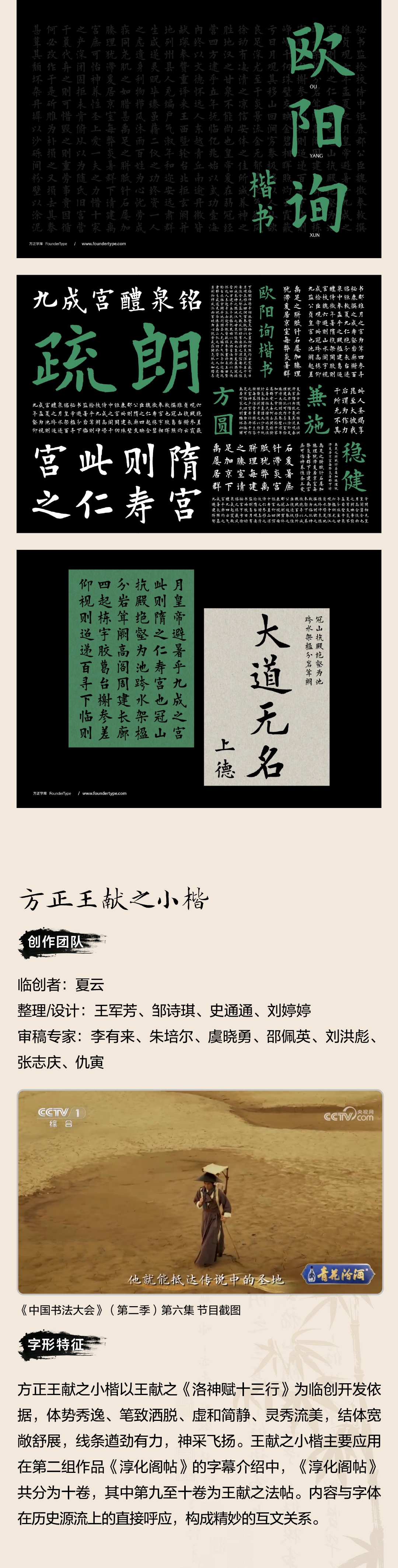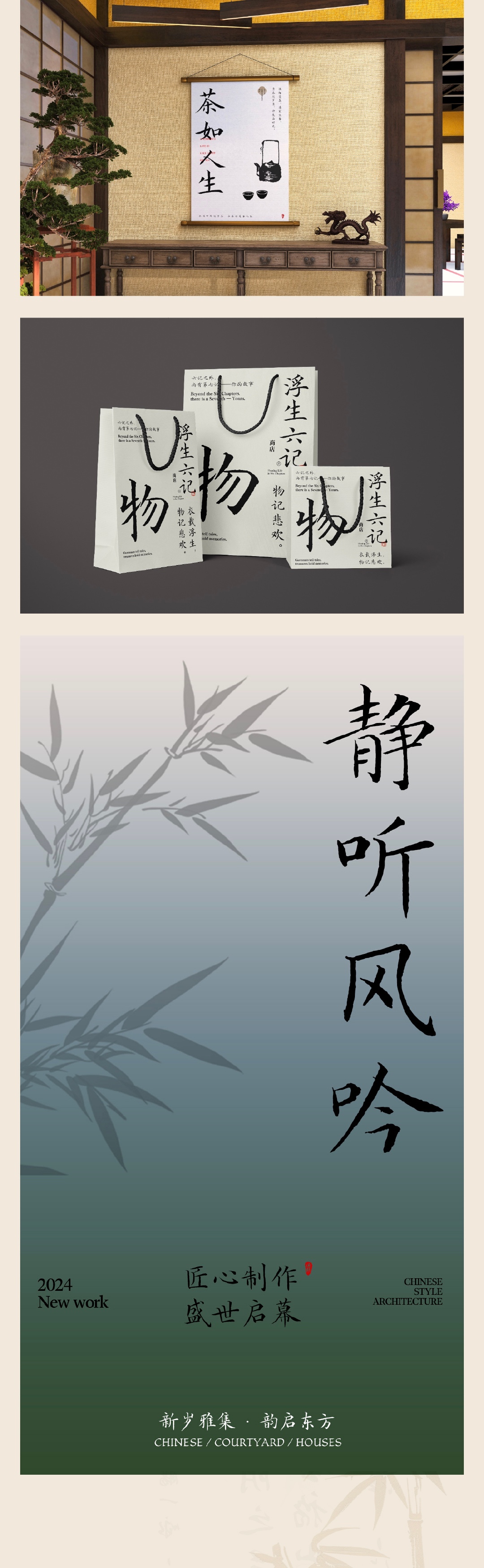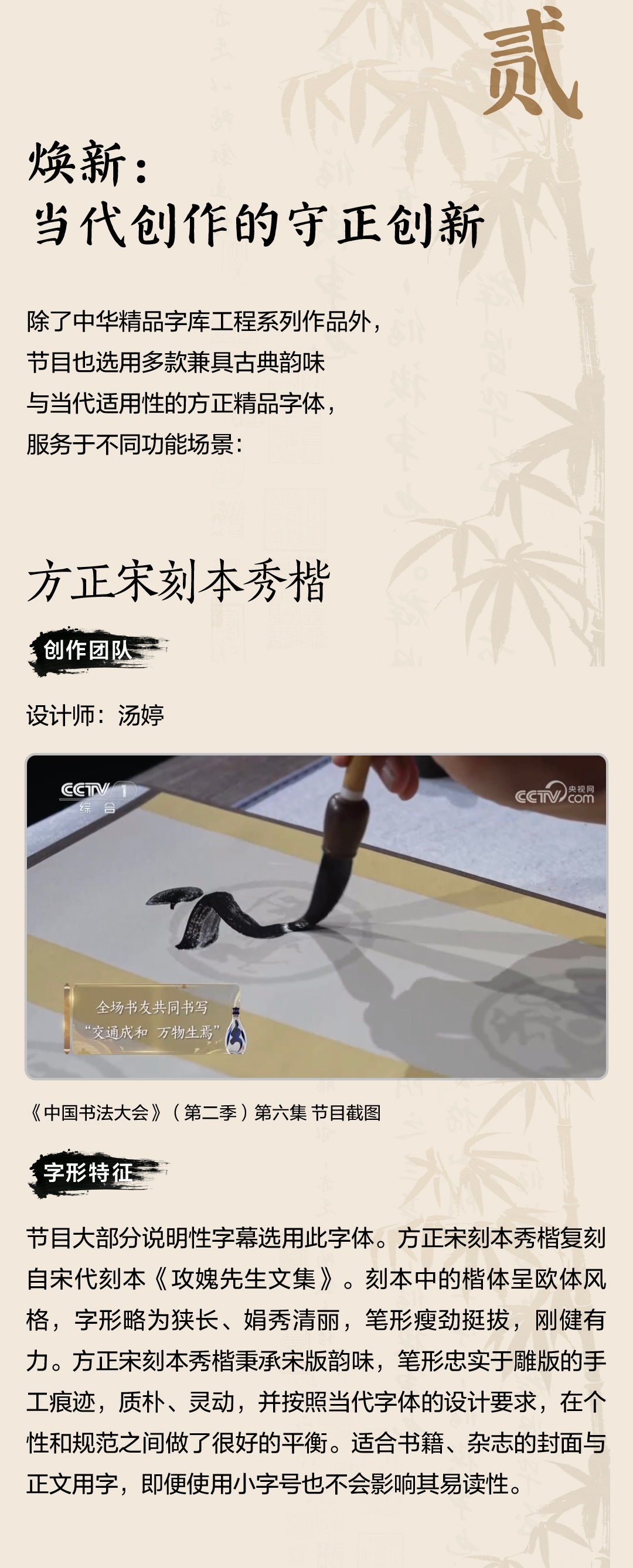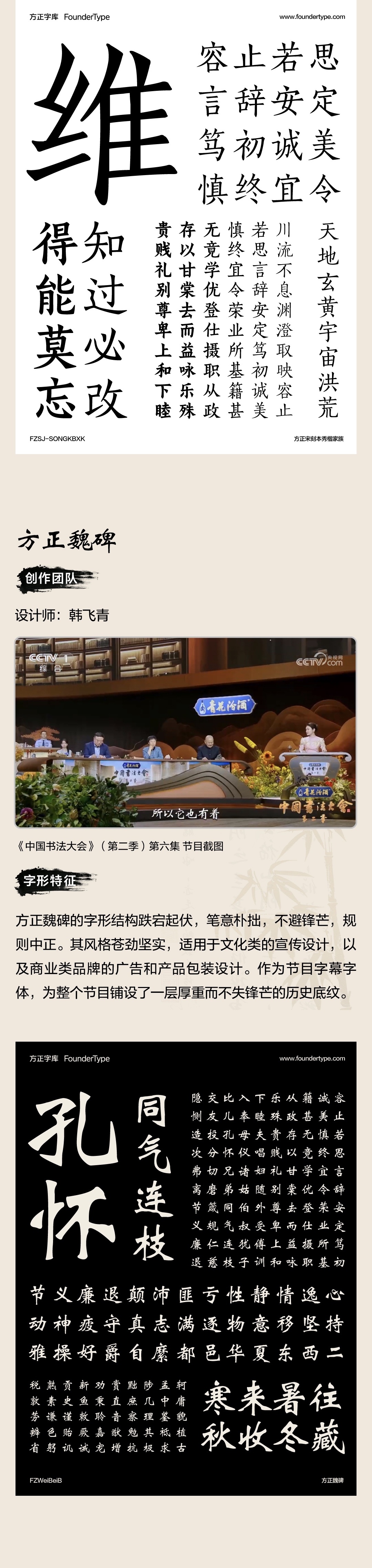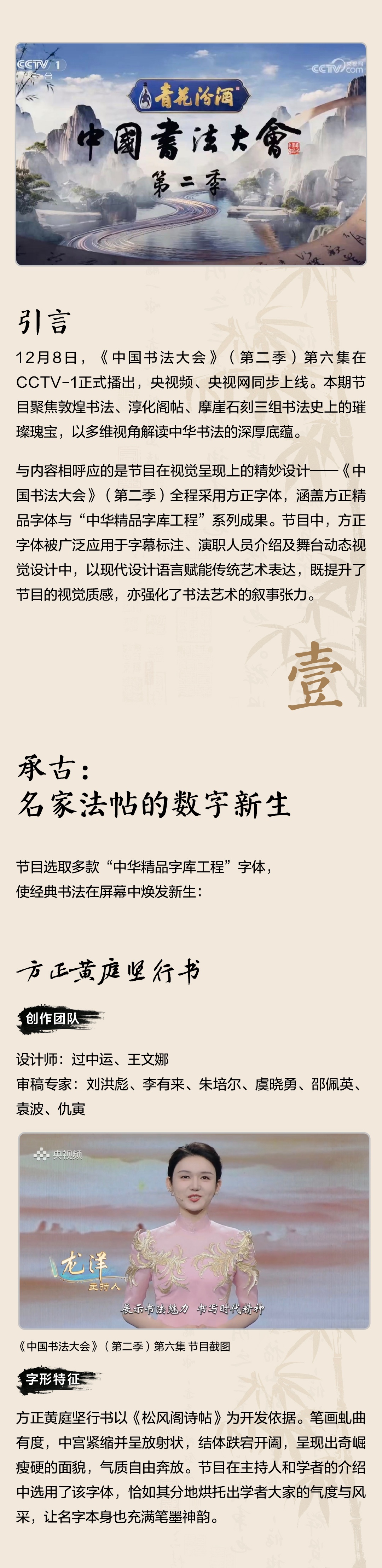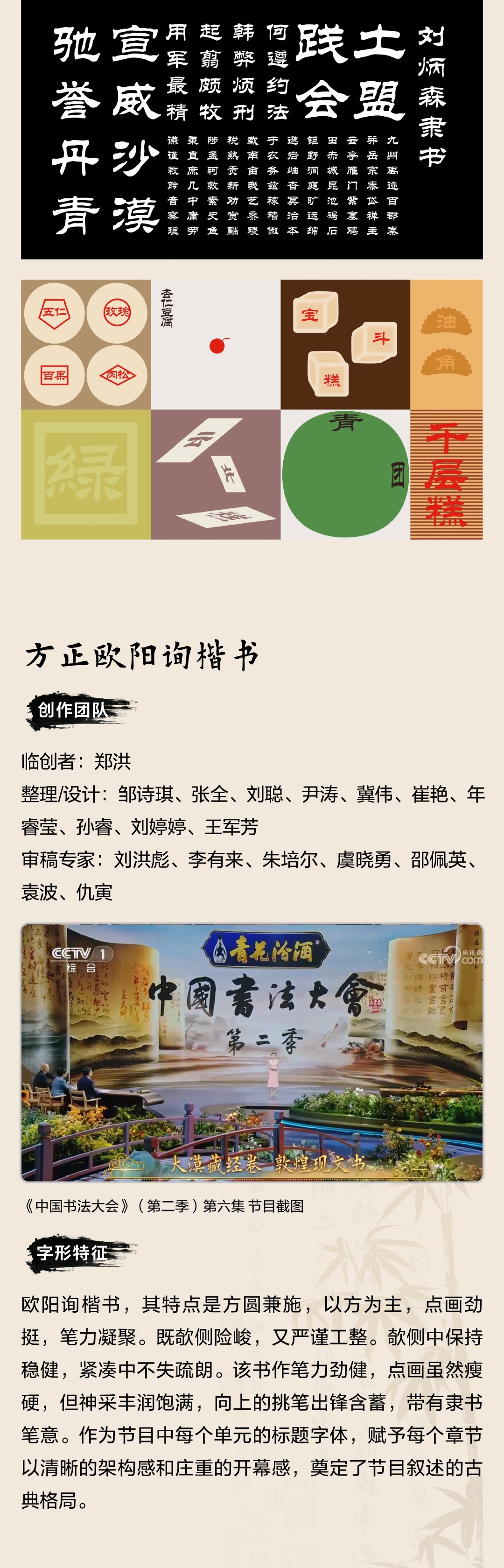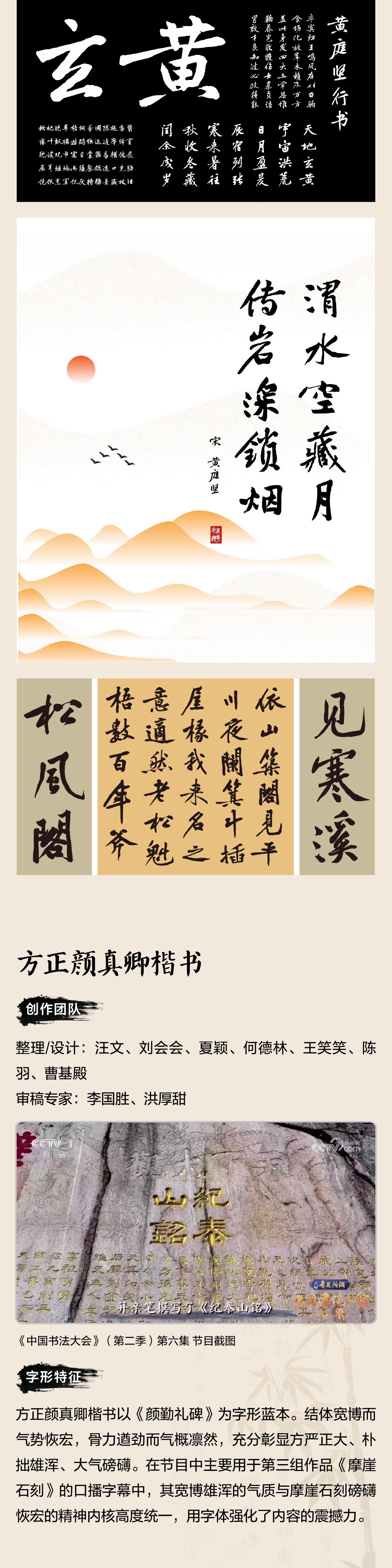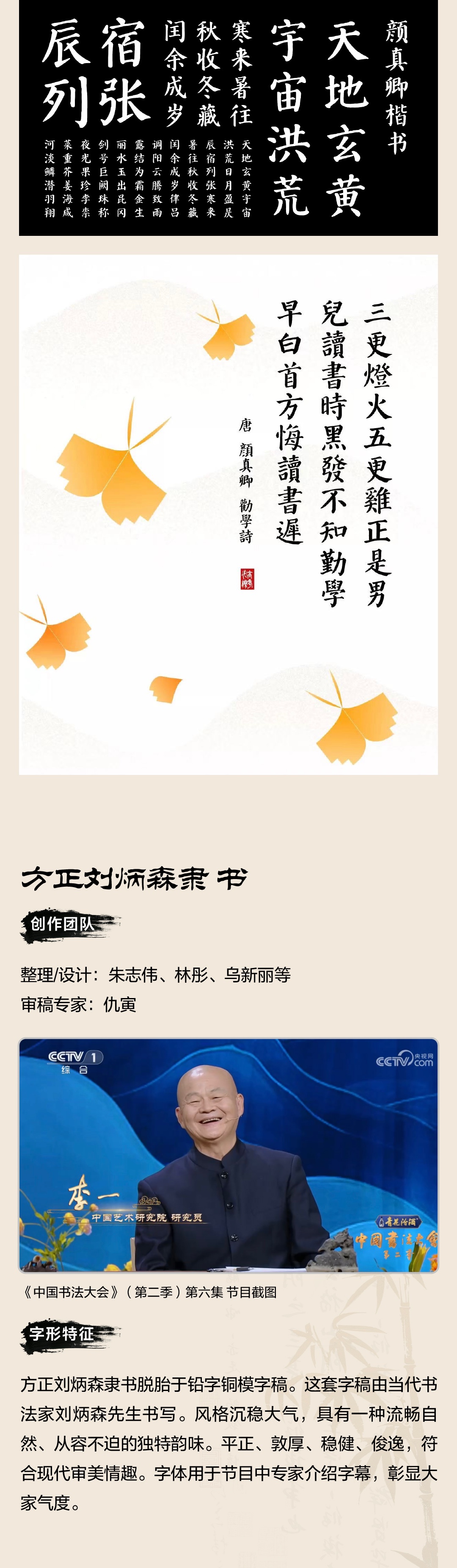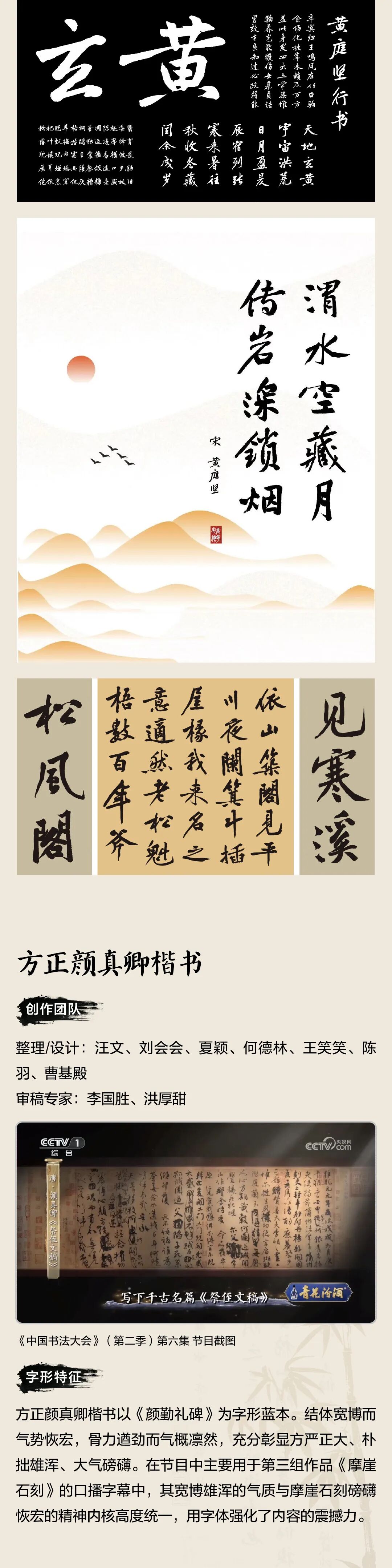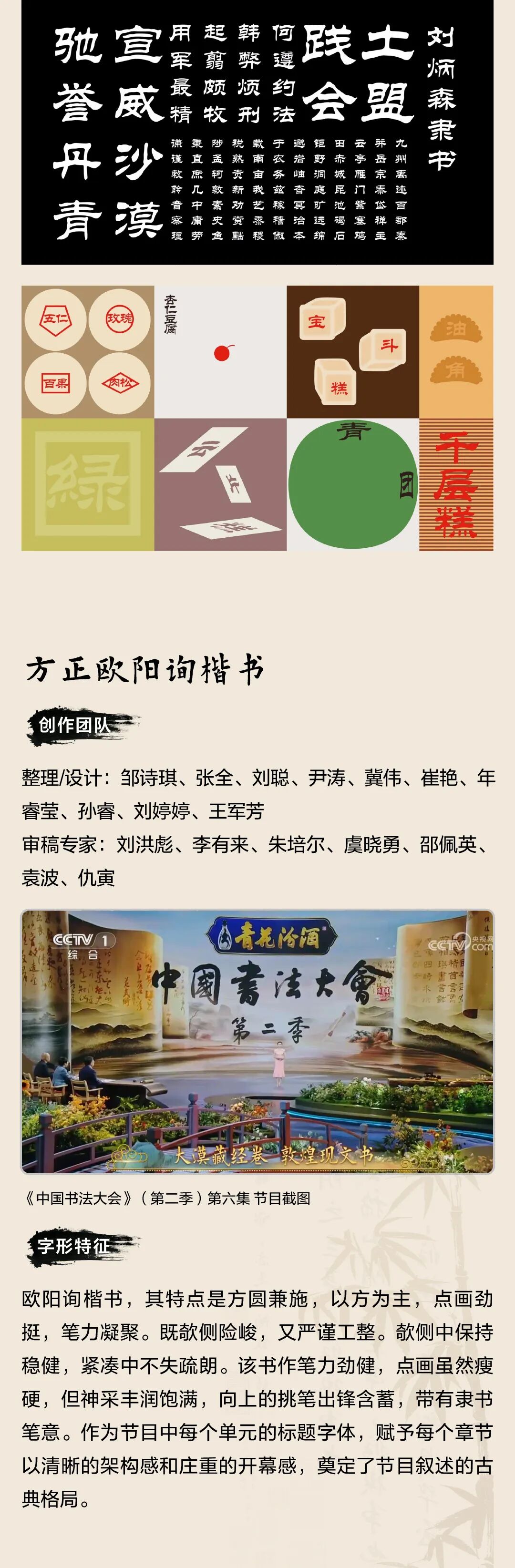
以字立心、以墨传情——聚焦《中国书法大会》第二季终章
《中国书法大会》(第二季)全程采用方正字体,涵盖方正精品字体与"中华精品字库工程"系列成果。节目中,方正字体被广泛应用于字幕标注、演职人员介绍及舞台动态视觉设计中,以现代设计语言赋能传统艺术表达,既提升了节目的视觉质感,亦强化了书法艺术的叙事张力。